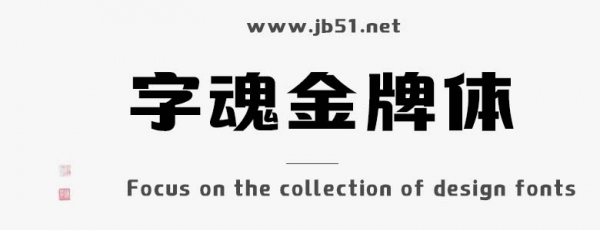
字魂金牌體是由字魂字庫(kù)推出的商用的黑體,該字體包含7144個(gè)中文、字母、 符號(hào)和數(shù)字,具有時(shí)尚的風(fēng)格,適合應(yīng)用于藝術(shù)設(shè)計(jì)、平面宣傳設(shè)計(jì)、網(wǎng)頁(yè)設(shè)計(jì),書法字帖等領(lǐng)域。
字魂金牌體字體是一款商用的黑體字體,該字體包含7144個(gè)中文、字母、 符號(hào)和數(shù)字,具有時(shí)尚的風(fēng)格,可以滿足您設(shè)計(jì)上的各種需求,該字體主要用于游戲動(dòng)漫等場(chǎng)景, 您不但可以在字魂網(wǎng)下載字魂金牌體字體,同時(shí)還有眾多毛筆書法字體、創(chuàng)意字體等可供選擇!